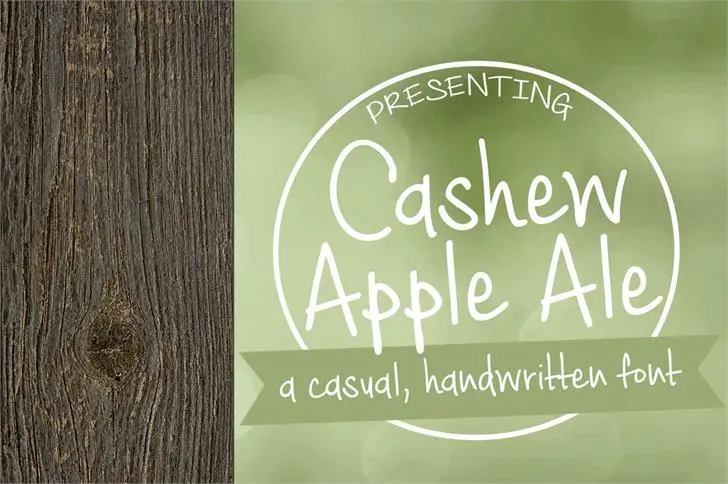
Cashew Apple Ale font – Download Grátis
A Cashew Apple Ale font é uma elegante e versátil escolha para projetos que exigem uma aparência clean e moderna. Desenvolvida por Hamilton, essa fonte sans-serif tem um caráter minimalista que transmite eficiência e simplicidade, perfeitamente adequada para aplicativos digitais e materiais de design gráfico. Ideal tanto para ambientes pessoais quanto para uso não-profit, sua natureza fluida permite o ajuste suave entre linhas mais largas e finas, adaptando-se facilmente a diferentes estilos de texto. Para aplicações comerciais que buscam uma maior flexibilidade com a fonte, Hamilton oferece opções de licenciamento adicional. Seja você um designer freelancer, uma empresa ou até mesmo um estudante, essa font pode atender às suas necessidades criativas sem comprometer seu orçamento. Não perca esta oportunidade de trazer um toque único e moderno ao seu próximo projeto visual com a Cashew Apple Ale font.